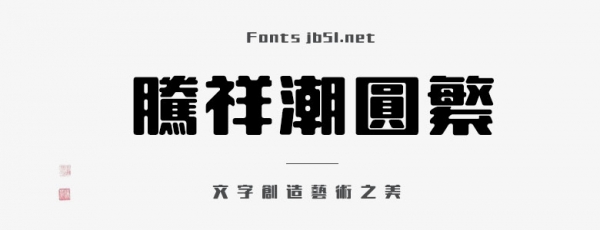
騰祥潮圓繁是一款不錯的藝術(shù)字體,由騰祥字庫出品,字體筆觸粗實,字字形結(jié)構(gòu)扁方、端莊,橫豎筆畫粗細比例適度、豎筆粗壯有力感,適合應(yīng)用于藝術(shù)設(shè)計、平面宣傳設(shè)計、網(wǎng)頁設(shè)計,書法字帖等領(lǐng)域,需要的朋友可以前來本站下載。
潮圓是一款富于變化的美術(shù)類黑體,是在潮黑的基礎(chǔ)上變換設(shè)計而成。雖然字形結(jié)構(gòu)與潮黑相同,但兩款字的風(fēng)格氣質(zhì)截然不同。潮圓將潮黑的棱角柔化形成被融化之感,融化了的筆畫圓潤富于親和力。字形結(jié)構(gòu)扁方、端莊,橫豎筆畫粗細比例適度、豎筆粗壯有力,布白均勻、行文貫通。潮圓筆畫簡潔圓潤細微處變換靈動,即實用又富有裝飾效果。適合標(biāo)題用字,可用于印刷出版、包裝設(shè)計、廣告設(shè)計、網(wǎng)頁設(shè)計等。